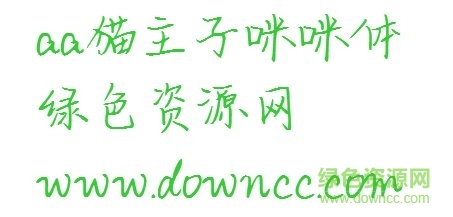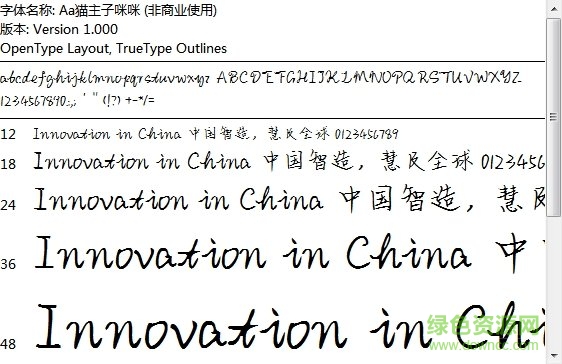
貓主子咪咪體出自aa字體管家字庫,造型有著貓爪般的尖銳,也有著貓咪的調(diào)皮可愛,給人十分清晰和諧的視覺體驗,快來綠色資源網(wǎng)下載收藏吧!
娟秀流暢,筆鋒婉轉,較細的線條勾勒出字體骨架,立而不失圓潤,柔而不失風骨。幾分清麗,幾分可愛,一股清新文藝風撲面而來。
貓主子咪咪體一款手寫風格的硬筆書法字體,字體瀟灑大方,流暢自如,可以廣泛運用在藝術設計、平面設計、海報設計、包裝設計等多種場合!